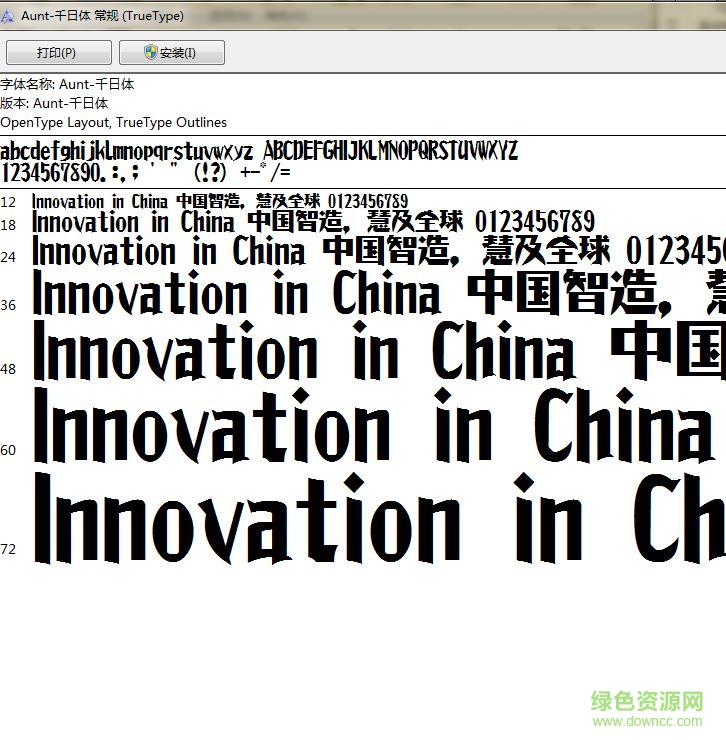
千日體ttf通過不斷的演變,讓看起來十分喜愛,這款字體的特色在于擁有十分渾厚的書寫視覺效果,讓你感受到十分不錯的粗體字體體驗,快來綠色資源網(wǎng)下載吧!
這款字體也支持日文字體的輸入,同時讓你感受到中文字體的濃厚字體效果,擁有十分不錯的字體表現(xiàn)效果,應用范圍十分廣泛,可以應用到影視制作行業(yè)中!